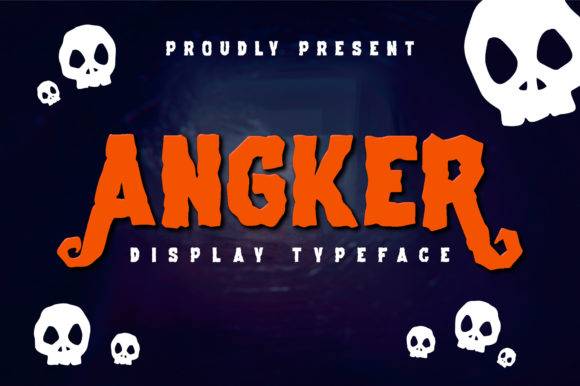
Fonte Angker para projetos de artesanato, logotipos e impressão.
Este arquivo contém uma fonte exclusiva, criada para design visual de alto impacto em projetos de artesanato e identidade visual comercial. Ela se enquadra na categoria de entidades de fonte, atendendo a diversas necessidades estilísticas, desde a criação de logotipos marcantes até layouts de impressão arrojados.
A fonte Angker oferece um apelo moderno e robusto, tornando-a adequada para materiais de produção de nível profissional, etiquetas de merchandising e aplicações gráficas onde uma tipografia que chame a atenção é essencial.
É particularmente eficaz em fluxos de trabalho de mídia mista que combinam impressão, recorte e aplicação de vinil.
Para quem é indicado?
- Designers gráficos com foco em branding.
- Pequenos empresários criando sinalização ou rótulos de produtos
- Artesãos que trabalham com corte a laser ou vinil
- Educadores criam materiais didáticos inovadores
- criadores de produtos e artigos para o público em geral
O que você pode fazer
- Logotipos de marcas e kits de identidade visual
- Rótulos de produtos e designs de embalagens
- Adesivos de vinil e estampas termocolantes
- Materiais de marketing impressos, como folhetos e cartazes.
- Produtos personalizados, incluindo canecas e sacolas de pano.
Por que você vai adorar
- A estrutura robusta garante visibilidade e legibilidade.
- Uso flexível em branding, sinalização e merchandising.
- Fácil de combinar com outras fontes em suítes de design.
| Recurso | Fonte Angker | Fonte Genérica A | Fonte Genérica B |
| Estilização | Ousado, estruturado, moderno | Fonte sem serifa simples | Serifa arredondada |
| Melhor uso | Criação, identidade visual, impressão | Texto do corpo | Faixas de manchete |